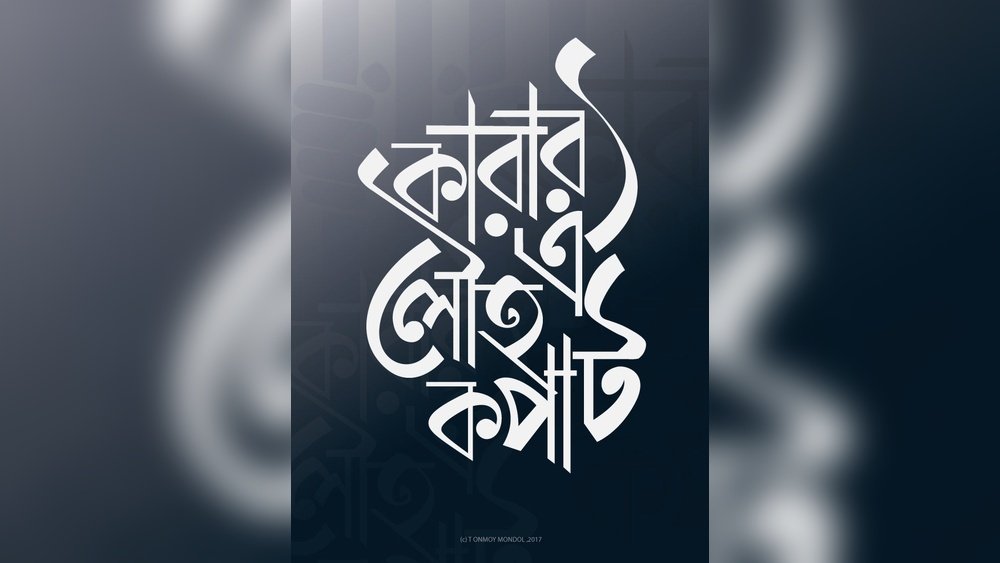
বাংলা ক্যালিগ্রাফি ফন্ট: নান্দনিকতার নতুন অধ্যায়
বাংলা ক্যালিগ্রাফি ফন্ট আমাদের জীবনের নানা ক্ষেত্রে নতুন মাত্রা যোগ করেছে। ডিজিটাল দুনিয়ায় বাংলা লেখা এখন আর শুধু টাইপোগ্রাফি বা সাধারণ টাইপফেসে সীমাবদ্ধ নয়। ক্যালিগ্রাফি ফন্টের মাধ্যমে আমরা এখন বাংলা ভাষার আবেগ, নান্দনিকতা ও শৈল্পিক প্রকাশ সহজেই ফুটিয়ে তুলতে পারি। ক্যালিগ্রাফি মানে শুধু সুন্দর হাতের লেখা নয়—এটি একটি শিল্প। বর্তমান সময়ে ডিজিটাল ডিজাইন, গ্রাফিক্স, সোশ্যাল মিডিয়া পোস্ট, ব্র্যান্ড লোগো, আমন্ত্রণপত্র, বইয়ের প্রচ্ছদ, এমনকি ভিডিও শিরোনামেও বাংলা ক্যালিগ্রাফি ফন্টের জনপ্রিয়তা বাড়ছে।
কিন্তু ক্যালিগ্রাফি ফন্ট বাছাই, ব্যবহার ও এর যথাযথ প্রয়োগ সম্পর্কে সঠিক ধারণা না থাকলে অনেকেই চমৎকার ডিজাইনের সুযোগ হারান। আজকের এই নিবন্ধে বাংলা ক্যালিগ্রাফি ফন্টের ধরন, জনপ্রিয় ফন্ট, ব্যবহার পদ্ধতি, ডিজাইন টিপস, এবং আরও অনেক গুরুত্বপূর্ণ বিষয় নিয়ে বিস্তারিত আলোচনা করা হবে।
বাংলা ক্যালিগ্রাফি ফন্ট কী ও কেন জনপ্রিয়
বাংলা ক্যালিগ্রাফি ফন্ট মানে এমন টাইপফেস, যা হাতে লেখা সুন্দর অক্ষরের আদলে ডিজাইন করা। ক্যালিগ্রাফি ফন্টের মূল বৈশিষ্ট্য হলো এতে হাতে লেখা লেখার প্রাণবন্ততা, আবেগ এবং শৈল্পিকতা দেখা যায়। বাংলার হাজার বছরের সংস্কৃতি, শিল্প ও লোকজ ধারার ছোঁয়া এতে স্পষ্ট। ডিজিটাল যুগে বাংলা লেখার জন্য অনেক স্টাইলের ফন্ট থাকলেও ক্যালিগ্রাফি ফন্ট আলাদা করে চেনা যায় তাদের কারুকার্য ও নান্দনিকতায়।
ক্যালিগ্রাফি ফন্টের জনপ্রিয়তা দ্রুত বাড়ছে, কারণ এর মাধ্যমে বাংলার আবেগ ও সংস্কৃতি আরও সুন্দরভাবে ফুটে ওঠে। ডিজাইন বা বিজ্ঞাপনের ক্ষেত্রে আপনি যখন সাধারণ টাইপফেস ব্যবহার করেন, তখন লেখাটির ভাষা প্রকাশ পেলেও, ক্যালিগ্রাফি ফন্ট ব্যবহারে লেখার ভেতরে বিশেষ ধরনের অনুভূতি, গল্প বা এক্সপ্রেশন চলে আসে। বাংলার উৎসব, সাহিত্য, কিংবা সামাজিক যোগাযোগ মাধ্যম—প্রত্যেক ক্ষেত্রে এই ফন্টের ব্যবহার দিন দিন বাড়ছে।
আরও একটি গুরুত্বপূর্ণ কারণ, ক্যালিগ্রাফি ফন্ট সহজেই চোখে পড়ে এবং মনোযোগ ধরে রাখে। সোশ্যাল মিডিয়ার ভিড়ে আপনার পোস্ট বা ডিজাইন আলাদা হতে চাইলে ক্যালিগ্রাফিক ফন্ট দারুণ কার্যকর। এই ফন্টে বাংলা শব্দগুলো আরও জীবন্ত ও শিল্পগুণে ভরা মনে হয়। অনেকেই কেবল শখের বশে নিজের নাম ক্যালিগ্রাফি ফন্টে লিখে ফেসবুকে বা ইনস্টাগ্রামে শেয়ার করেন। এই চর্চা দিন দিন জনপ্রিয় হচ্ছে।
অনেকে মনে করেন, বাংলা ক্যালিগ্রাফি ফন্ট মানেই শুধু হাতে লেখা স্টাইল। কিন্তু এর চেয়ে বড় ব্যাপার হলো—এতে বাংলার ঐতিহ্য, সংস্কৃতি, লোকজ ছন্দ, আধুনিকতা ও বৈচিত্র্য সব কিছুই একসাথে মিশে যায়। ডিজিটাল মার্কেটিং, ব্র্যান্ডিং, গ্রাফিক ডিজাইন, ভিডিও এডিটিং—সবক্ষেত্রেই এর উপস্থিতি বাড়ছে। শুধু সৌন্দর্যের জন্য নয়, বাংলা ভাষার নিজস্ব আবেগ ও পরিচিতি প্রকাশ করতেও ক্যালিগ্রাফি ফন্ট অপরিহার্য হয়ে উঠেছে।
বাংলা ক্যালিগ্রাফি ফন্টের মূল বৈশিষ্ট্য
ক্যালিগ্রাফি ফন্টের কিছু মৌলিক বৈশিষ্ট্য আছে, যেগুলো সাধারণ টাইপফেস থেকে একে আলাদা করে। এই বৈশিষ্ট্যগুলো জানলে ফন্ট বাছাইয়ে সুবিধা হবে এবং ডিজাইনেও নতুনত্ব আসবে।
- হাতে লেখা স্টাইল: ক্যালিগ্রাফি ফন্টের অক্ষর দেখতে মনে হয়, যেন কারও হাতে লেখা। এতে লেখার ভেতরে প্রাণ ও নান্দনিকতা চলে আসে। এই হাতে লেখা স্টাইল কখনও সোজা, কখনও বাঁকা, কখনও আবার একটু এলোমেলোও হতে পারে।
- স্ট্রোকের ভিন্নতা: বাংলা ক্যালিগ্রাফি ফন্টে মোটা ও পাতলা স্ট্রোকের মিশ্রণ থাকে। কিছু অক্ষরের শুরুতে বা শেষে স্ট্রোক মোটা, কিছু অক্ষরের মাঝে পাতলা রেখা দেখা যায়। এই বৈচিত্র্য পুরো লেখাকে আরও আকর্ষণীয় করে তোলে।
- লতাপাতা বা অলঙ্করণ: অনেক ক্যালিগ্রাফি ফন্টে অক্ষরের সাথে লতাপাতা, ফ্লাওয়ার, বা বিভিন্ন অলঙ্কার যোগ করা হয়। এগুলো কখনও অক্ষরের নিচে, কখনও পাশে, কখনও পুরো লেখার চারপাশে থাকে। এই অলঙ্করণ বাংলা ক্যালিগ্রাফি ফন্টের এক বিশেষ বৈশিষ্ট্য।
- কিছুটা অসমতা: সাধারণ টাইপফেসে সব অক্ষর একরকম, কিন্তু ক্যালিগ্রাফি ফন্টে কখনও কখনও এক অক্ষরের রূপ আরেক অক্ষরের থেকে একটু আলাদা হয়। এই অসমতা লেখাকে আরও স্বতঃস্ফূর্ত ও শিল্পময় করে তোলে। এতে হাতে লেখা ‘ইম্পারফেকশন’-এর সৌন্দর্য ফুটে ওঠে।
- নান্দনিক স্পেসিং: অক্ষরের মাঝে ও লাইনের মাঝে ফাঁকা জায়গা যত্ন নিয়ে ঠিক করা হয়। এতে পুরো লেখার ভারসাম্য (balance) বজায় থাকে। স্পেসিং ঠিক না হলে ফন্ট দেখতে অগোছালো লাগতে পারে।
- বৈচিত্র্যপূর্ণ যুক্তাক্ষর: অনেক ক্যালিগ্রাফি ফন্টে বিশেষভাবে ডিজাইন করা যুক্তাক্ষর থাকে। এতে ফন্টের ইউনিকনেস বাড়ে, এবং বাংলা লেখার জটিলতা আরও সহজভাবে প্রকাশ করা যায়।
- মানানসই মাত্রা ও কার: বাংলা ভাষায় ‘মাত্রা’ ও ‘কার’ খুব গুরুত্বপূর্ণ। ক্যালিগ্রাফি ফন্টে এগুলোকে আরও সুন্দর ও নান্দনিকভাবে উপস্থাপন করা হয়। কখনও মাত্রা একটু বাঁকা বা ফুলের মতো আকৃতিতে থাকে।
এছাড়া, ক্যালিগ্রাফি ফন্টে কখনও কখনও অক্ষরের শুরুর দিকে বা শেষে বিশেষ ধরনের টেইল, সুইশ, বা কার্ভ যোগ করা হয়, যা লেখাকে আরও স্টাইলিশ করে তোলে।
জনপ্রিয় বাংলা ক্যালিগ্রাফি ফন্টসমূহ
বাংলা ক্যালিগ্রাফি ফন্টের সংখ্যা দিন দিন বাড়ছে এবং এর বৈচিত্র্যও ক্রমশ বৃদ্ধি পাচ্ছে। বর্তমানে কিছু ফন্ট ডিজাইনার ও ডিজাইন প্ল্যাটফর্ম দারুণ সুন্দর ও ইউনিক ক্যালিগ্রাফি ফন্ট তৈরি করছেন। এখানে সবচেয়ে জনপ্রিয় ও বহুল ব্যবহৃত কিছু ফন্ট নিয়ে বিস্তারিত আলোচনা করা হলো, যাতে আপনি আপনার ডিজাইনের জন্য সঠিক ফন্ট বাছাই করতে পারেন।
১. ক্যালিগ্রাফি বাংলা
‘ক্যালিগ্রাফি বাংলা’ ফন্টটি ডিজাইন জগতে একটি সুপরিচিত নাম। এই ফন্টে আপনি পেয়ে যাবেন হাতে লেখা স্টাইলের নিখুঁত প্রতিচ্ছবি। অক্ষরের মধ্যে মোটা-পাতলা স্ট্রোকের অসাধারণ কম্বিনেশন, কিছু অক্ষরে হালকা অলঙ্করণ, এবং বর্ণের মাঝে ভারসাম্যপূর্ণ স্পেসিং—সব মিলিয়ে এটি খুবই পেশাদার মানের ফন্ট। সোশ্যাল মিডিয়া পোস্ট, ডিজিটাল ব্যানার, বা ব্র্যান্ড লোগো ডিজাইনে এই ফন্টটি ব্যাপকভাবে ব্যবহৃত হয়।
অনেক ডিজাইনার এই ফন্ট পছন্দ করেন কারণ, এটি খুব সহজেই চোখে পড়ে এবং বাংলা ভাষার আবেগ প্রকাশে কার্যকর। বিশেষ করে, লেখার শুরু ও শেষের স্ট্রোকগুলোতে হাতে লেখা ফ্লো স্পষ্টভাবে দেখা যায়। আপনি চাইলে এই ফন্ট বিভিন্ন কালারে ব্যবহার করতে পারেন এবং একই ডিজাইনকেও ভিন্নভাবে উপস্থাপন করতে পারবেন।
২. জ্যোতি ক্যালিগ্রাফি
‘জ্যোতি ক্যালিগ্রাফি’ ফন্টের অক্ষরগুলো দেখতে অনেকটা ব্রাশ দিয়ে আঁকা মনে হয়। এতে রয়েছে মুক্তভাবে আঁকা স্টাইল, যেখানে কিছু অক্ষর একটু বাঁকা, কিছুটা ঢেউ খেলানো। এই ফন্ট বিশেষভাবে সাহিত্য ম্যাগাজিন, পত্রিকা কিংবা আমন্ত্রণপত্রে ব্যবহার হয়। ব্রাশ স্ট্রোকের নান্দনিক বৈচিত্র্য, সাথে অক্ষরের মাঝে নরম স্পেসিং—সব মিলিয়ে এটি অনেকের পছন্দের তালিকায়।
জ্যোতি ক্যালিগ্রাফি ফন্টের আরেকটি বিশেষ দিক হলো—এতে যুক্তাক্ষর ও মাত্রা খুব সুন্দরভাবে ফুটে ওঠে। ফলে, আপনি যদি বড় আকারের শিরোনাম বা কবিতার জন্য ফন্ট খুঁজছেন, এটি হতে পারে আদর্শ পছন্দ।
৩. বাংলা ক্যালিগ্রাফি স্টাইল
এটি একটি ফ্রি ফন্ট, যা আপনি Fontlipi থেকে সহজেই ডাউনলোড করতে পারেন। এই ফন্টে আধুনিক ডিজাইনের ছোঁয়া থাকলেও, ক্লাসিক ক্যালিগ্রাফির সৌন্দর্য বজায় আছে। অক্ষরগুলো সাধারণত একটু লম্বা, এবং স্ট্রোকের মধ্যে হালকা কার্ভ বা বাঁক দেখা যায়। ডিজিটাল আর্ট, পোস্টার ডিজাইন, বা সোশ্যাল মিডিয়া থাম্বনেইলে এটি দারুণ মানানসই।
ফন্টটির ফ্রি ভার্সন থাকায়, নতুন ডিজাইনার বা শিক্ষার্থীরাও সহজে এটি ব্যবহার করতে পারেন। এছাড়া, ফন্টের ফাইল ছোট এবং ইনস্টল করা সহজ।
Read Also: মাহফুজ লিপি বাংলা প্রিমিয়াম ফন্ট: স্টাইলিশ এবং প্রফেশনাল ডিজাইন
৪. রঙিন ক্যালিগ্রাফি
‘রঙিন ক্যালিগ্রাফি’ ফন্টে অক্ষরগুলো স্পষ্ট ও বড়, বিশেষ করে শিরোনাম বা হেডিং ডিজাইনের জন্য তৈরি। এই ফন্টের বিশেষত্ব হলো—কিছু অক্ষরের নিচে বা পাশে আলংকারিক ডিজাইন (যেমন লতাপাতা, ফুল) দেয়া থাকে, যা সাধারণ ফন্ট থেকে একে আলাদা করে। পোস্টার, ব্যানার, ম্যাগাজিনের হেডিং কিংবা ইউটিউব ভিডিওর নাম লেখার জন্য এটি বেশ উপযোগী।
এটি ব্যবহার করলে আপনার ডিজাইন অনেক বেশি আকর্ষণীয় হবে, তবে বডি টেক্সটে ব্যবহার করলে পড়তে একটু কষ্ট হতে পারে।
৫. আর্টিস্টিক বাংলা
এই ফন্টটি হাতে লেখা অনুভূতি দেয় এবং ব্রাশ স্ট্রোকের মতো মোটা-পাতলা লাইনের মিশ্রণ রয়েছে। অক্ষরগুলো দেখতে একটু এলোমেলো, কিন্তু তাতেই রয়েছে শিল্প-সৌন্দর্য। পোস্টার, ব্যানার, আর্ট ওয়ার্ক—এই সব ডিজাইনেই এটি আদর্শ। বিশেষ করে, যারা হাতে লেখা চিঠি বা কবিতার অনুভূতি ডিজাইনে আনতে চান, তাদের জন্য এই ফন্ট অসাধারণ।
এছাড়া, এই ফন্টটি ছোট বা বড়—যেকোনো সাইজে ব্যবহার করা যায় এবং অক্ষরের স্পেসিংও খুব সুন্দরভাবে ডিজাইন করা।
৬. স্টাইলিশ ক্যালিগ্রাফি
‘স্টাইলিশ ক্যালিগ্রাফি’ ফন্ট আধুনিক ও ট্র্যাডিশনাল ক্যালিগ্রাফি ঢঙের মিশ্রণ। ডিজিটাল বিজ্ঞাপন, সোশ্যাল মিডিয়া পোস্ট, ইউটিউব থাম্বনেইল, কিংবা ব্র্যান্ড লোগো—সবক্ষেত্রেই এটি কার্যকর। এই ফন্টের অক্ষরগুলো একটু টুইস্টেড, কিছু অক্ষরে স্টাইলিশ কার্ভ বা সুইশ আছে। ফলে, আপনি চাইলে একই ফন্ট দিয়ে একাধিক ডিজাইন স্টাইল তৈরি করতে পারবেন।
৭. হস্তলিপি ক্যালিগ্রাফি
এটি মূলত হাতে লেখা স্টাইলের ওপর ভিত্তি করে তৈরি। অক্ষরগুলো দেখতে মনে হবে, যেন কেউ দ্রুত অথচ সুন্দরভাবে লিখেছে। ব্যক্তিগত আমন্ত্রণপত্র, কবিতা, চিঠির ডিজাইন কিংবা সোশ্যাল মিডিয়া কোটেশন—সবক্ষেত্রেই এই ফন্ট মানানসই। এই ফন্ট ব্যবহার করলে ডিজাইনে ব্যক্তিগত স্পর্শ (personal touch) আসে।
৮. ডিজাইন বাংলা ক্যালিগ্রাফি
এখানে ক্লাসিক ও মডার্ন স্টাইলের মিশ্রণ রয়েছে। অক্ষরগুলোতে মাঝে মাঝে অতিরিক্ত অলঙ্করণ থাকলেও পড়তে সহজ। তাই সোশ্যাল মিডিয়া গ্রাফিক্স, ওয়েবসাইট হেডার, বিজ্ঞাপন ডিজাইন—সবখানেই এটি ব্যবহৃত হয়। ফন্টের ভারসাম্যপূর্ণ স্পেসিং এবং ইউনিক স্টাইলের কার্ভ ডিজাইনকে আরও আকর্ষণীয় করে তোলে।
৯. ব্রাশ ক্যালিগ্রাফি বাংলা
ব্রাশ দিয়ে আঁকা অক্ষরের মতো এই ফন্টের ডিজাইন। মোটা ও পাতলা স্ট্রোকের অসাধারণ কম্বিনেশন, এবং অক্ষরের মাঝে নান্দনিক স্পেসিং, ফলে ডিজিটাল আর্ট, ফটো এডিটিং, বা ভিডিও শিরোনামে এটি জনপ্রিয়। বিশেষ করে, যারা হাতে লেখা ব্রাশ-স্টাইল ফন্ট পছন্দ করেন, তাদের জন্য এটি আদর্শ।
১০. ইউনিক বাংলা ক্যালিগ্রাফি
প্রতিটি অক্ষরে ইউনিকনেস আছে। সাধারণত ব্র্যান্ড লোগো, টাইটেল ডিজাইন, বইয়ের প্রচ্ছদ, বা বিশেষ দিবসের পোস্টে ব্যবহৃত হয়। এই ফন্টের বিশেষত্ব হলো—একই অক্ষর বারবার হলেও, প্রতিবার নতুনভাবে ডিজাইন করা। ফলে, পুরো লেখাটা দেখতে আরও শিল্পময় লাগে।
বাংলা ক্যালিগ্রাফি ফন্ট নির্বাচন করার নিয়ম
সঠিক ফন্ট নির্বাচন ডিজাইনের জন্য খুব গুরুত্বপূর্ণ। অনেক সময় দেখা যায়, সুন্দর লেখার চেয়ে উপযোগী ফন্ট বেছে নেওয়াই আসল চ্যালেঞ্জ। ফন্টের সৌন্দর্য যেমন গুরুত্বপূর্ণ, তেমনি তার ব্যবহারিক দিকও বুঝে নিতে হয়। নিচে কিছু গুরুত্বপূর্ণ বিষয় তুলে ধরা হলো—
| বিষয় | কেন গুরুত্বপূর্ণ | পরামর্শ |
|---|---|---|
| ফন্টের পাঠযোগ্যতা | অত্যন্ত অলঙ্কারিক ফন্ট পড়তে সমস্যা হতে পারে | শিরোনাম ও ছোট লেখার জন্য ভিন্ন ফন্ট ব্যবহার করুন |
| উপযুক্ততা | সব ফন্ট সব ডিজাইনে মানায় না | কাজের ধরন অনুযায়ী ফন্ট বাছাই করুন |
| ফাইল ফরম্যাট | কিছু সফটওয়্যারে নির্দিষ্ট ফরম্যাটই সাপোর্ট করে | OTF/TTF ফরম্যাট সাধারণত বেশি ব্যবহারযোগ্য |
| লাইসেন্স | সব ফন্ট ফ্রি নয় | ব্যবহারের আগে লাইসেন্স চেক করুন |
নতুনদের জন্য দুইটি মূল্যবান টিপস
- অনেকেই শুধু সুন্দর দেখলেই ফন্ট বাছাই করেন। কিন্তু আসল কাজের জন্য ফন্টটি উপযোগী কিনা, সেই দিকটি খেয়াল করতে ভুলে যান। যেমন, বড় টেক্সটে অতিরিক্ত অলঙ্কার থাকলে পড়তে কষ্ট হয়।
- ফন্টের ভার্সন বা ফরম্যাট না মিললে অনেক সফটওয়্যারে ফন্ট সাপোর্ট নাও করতে পারে। তাই ডাউনলোড করার সময় আপনার সফটওয়্যারের উপযোগী ফরম্যাটটি বাছাই করুন।
আরেকটি গুরুত্বপূর্ণ বিষয়, ফন্ট নির্বাচনের সময় তার ফ্যামিলি, ওজন (weight), এবং ভার্সন দেখুন। অনেক সময় এক ফন্টের একাধিক ভার্সন থাকে—সেগুলো পরীক্ষা করে সেরা ভার্সনটি বাছাই করুন।
Credit: www.freepik.com
বাংলা ক্যালিগ্রাফি ফন্ট কোথায় পাবেন?
বর্তমানে অসংখ্য ওয়েবসাইটে ফ্রি ও প্রিমিয়াম বাংলা ক্যালিগ্রাফি ফন্ট পাওয়া যায়। ডিজাইন জগতে এই ওয়েবসাইটগুলো অনেক জনপ্রিয় কারণ, এখানে ফন্টের বৈচিত্র্য, মান, ও আপডেট সবই ভালো থাকে। কিছু সেরা সোর্স—
- Fontlipi (বেশিরভাগ ফ্রি ও মানসম্পন্ন ফন্ট)
- Google Fonts (বাংলা ফন্টের সংখ্যা কম, তবে কিছু ক্যালিগ্রাফি ফন্ট আছে)
- Behance (কিছু ফ্রি, কিছু পেইড ফন্ট)
- Creative Market (প্রিমিয়াম ফন্ট)
এছাড়াও, বিভিন্ন ফেসবুক গ্রুপ, ডিজাইন ফোরাম এবং টেলিগ্রাম চ্যানেলেও অনেক নতুন ফন্ট শেয়ার হয়। তবে, সব সময় অফিসিয়াল ওয়েবসাইট থেকে ডাউনলোড করা নিরাপদ।
Related: Bijoy Bangla Font Free Download: দ্রুত ও সহজ ফন্ট সংগ্রহ করুন!
ডাউনলোড করার সময় দেখুন, ফন্টটি ফ্রি, ফ্রি ফর কমার্শিয়াল ইউজ, না কি শুধু ব্যক্তিগত ব্যবহারের জন্য। লাইসেন্সের শর্ত জেনে নিন, কারণ অনেক সময় বাণিজ্যিক কাজে ব্যবহারে ক্রেডিট বা অনুমতি লাগতে পারে।
কিভাবে বাংলা ক্যালিগ্রাফি ফন্ট ব্যবহার করবেন
ডিজাইন সফটওয়্যারে বাংলা ক্যালিগ্রাফি ফন্ট ব্যবহার করা খুব সহজ। এখানে ধাপে ধাপে বর্ণনা করা হলো—
- প্রথমে পছন্দের ফন্টটি ডাউনলোড করুন (সাধারণত .zip ফাইল, ভিতরে .ttf বা .otf ফরম্যাটে)।
- ফন্ট ফাইলটি ওপেন করে ‘ইনস্টল’ বোতামে ক্লিক করুন।
- ইনস্টল হলে ফন্টটি স্বয়ংক্রিয়ভাবে আপনার কম্পিউটারের ফন্ট লিস্টে যুক্ত হবে।
- আপনার পছন্দের ডিজাইন সফটওয়্যার (যেমন: Photoshop, Illustrator, MS Word, Canva) ওপেন করুন।
- ফন্ট লিস্ট থেকে নতুন ক্যালিগ্রাফি ফন্টটি খুঁজে নিন এবং প্রয়োজনে সেট করুন।
- বাংলা কীবোর্ড ব্যবহার করে সহজেই লিখতে পারবেন।
উদাহরণ:
আপনি যদি Photoshop-এ নতুন ফন্ট ব্যবহার করতে চান, তাহলে প্রথমে ফন্ট ইন্সটল করে নিন। তারপর Photoshop ওপেন করলে ফন্ট লিস্টে নতুন ক্যালিগ্রাফি ফন্ট দেখা যাবে। বাংলা ভাষায় টাইপ করতে চাইলে বিজয়, অভ্র বা ইউনিজয় কীবোর্ড ব্যবহার করুন।
মোবাইলে ক্যালিগ্রাফি ফন্ট ব্যবহার
এন্ড্রয়েড বা আইফোনে কাস্টম ফন্ট ব্যবহারের জন্য কিছু অ্যাপ যেমন Phonto, Pixellab, Canva ইত্যাদি ব্যবহার করা যায়। অ্যাপে ফন্ট ইমপোর্ট অপশন থাকে। আপনি ফন্ট ফাইল ডাউনলোড করে অ্যাপে ইমপোর্ট করুন। এরপর ছবিতে বা ডিজাইনে সহজেই বাংলা ক্যালিগ্রাফি ফন্টে লিখতে পারবেন।
তবে, মোবাইলের সিস্টেম লেভেলে (অর্থাৎ পুরো ডিভাইসে) সাধারণত ফন্ট পরিবর্তন করা যায় না। কিছু কাস্টম লঞ্চার বা থিম ইঞ্জিনে ফন্ট চেঞ্জ করার অপশন থাকলেও, তা সব ফোনে কাজ নাও করতে পারে।
ফন্ট ইনস্টল করতে সমস্যা হলে কী করবেন?
- ফন্ট ফাইলটি ঠিকমতো ডাউনলোড হয়েছে কি না চেক করুন।
- ফাইলটি .ttf বা .otf ফরম্যাটে আছে কি না দেখুন।
- সফটওয়্যার বা অপারেটিং সিস্টেম আপডেট থাকলে ফন্ট ইন্সটল সহজ হয়।
- প্রয়োজনে ফন্টটি আবার ডাউনলোড করে ইনস্টল করুন।
বাংলা ক্যালিগ্রাফি ফন্টের ডিজাইন টিপস
ডিজাইনে ক্যালিগ্রাফি ফন্টের ব্যবহার মানেই নান্দনিকতা, তবে কিছু ভুল করলে পুরো ডিজাইন নষ্ট হতে পারে। আপনার ডিজাইন পেশাদার ও আকর্ষণীয় করতে চাইলে নিচের টিপসগুলো মানুন—
- মাত্রা ও স্পেসিং ঠিক রাখুন: ক্যালিগ্রাফি ফন্টে অনেক সময় অক্ষরের মাঝে বেশি বা কম স্পেস থেকে যায়। লিখার আগে ও পরে সব অক্ষর একবার দেখে নিন। বিশেষ করে, যুক্তাক্ষর ও মাত্রা ঠিকমতো দেখা যাচ্ছে কি না নিশ্চিত করুন।
- একাধিক ক্যালিগ্রাফি ফন্ট একসাথে ব্যবহার করবেন না: অনেকেই মনে করেন, একাধিক ক্যালিগ্রাফি ফন্ট এক ডিজাইনে দিলে আরও সুন্দর লাগবে। আসলে এতে ডিজাইন এলোমেলো হয়ে যায় এবং পাঠযোগ্যতা কমে যায়।
- কালার কনট্রাস্ট: ব্যাকগ্রাউন্ড ও ফন্টের রঙে যথেষ্ট কনট্রাস্ট রাখুন। ক্যালিগ্রাফি ফন্ট সাধারণত মোটা-পাতলা স্ট্রোকে হয়, ফলে হালকা রঙের ব্যাকগ্রাউন্ডে গাঢ় রঙের ফন্ট বা উল্টোটা ব্যবহার করুন।
- শিরোনাম ও বডি টেক্সটে ভিন্ন ফন্ট: ক্যালিগ্রাফি ফন্ট সাধারণত শিরোনামের জন্য ভালো; বডি টেক্সটে সাধারণ ফন্ট ব্যবহার করুন। এতে পাঠযোগ্যতা বাড়ে এবং ডিজাইন আরও ভারসাম্যপূর্ণ হয়।
- অলঙ্করণ বা লতাপাতা ব্যবহার: ফন্টে যদি অতিরিক্ত অলঙ্করণ থাকে, তবে ডিজাইনে কম ব্যবহার করুন। বেশি অলঙ্করণ হলে ফন্ট পড়তে কষ্ট হয় এবং ডিজাইন অগোছালো দেখায়।
- ড্রপ শ্যাডো বা গ্লো এফেক্ট যুক্ত করুন: ক্যালিগ্রাফি ফন্টের সৌন্দর্য বাড়াতে হালকা ড্রপ শ্যাডো, গ্লো বা আউটলাইন এফেক্ট দিতে পারেন। তবে খুব বেশি দিলে লেখা পড়তে কষ্ট হবে।
- ফন্ট সাইজ ঠিক রাখুন: শিরোনামে বড় ফন্ট ব্যবহার করুন, কিন্তু বেশি বড় করলে স্ট্রোক ব্লার হতে পারে। বডি টেক্সটে ছোট ফন্ট ব্যবহার করবেন না।
- স্পেশাল ক্যারেক্টার ও সিম্বল ব্যবহার: ক্যালিগ্রাফি ফন্টে অনেক সময় স্পেশাল ক্যারেক্টার (যেমন: ফুল, তারা, ইমোজি) আলাদাভাবে যুক্ত থাকে। প্রয়োজনে সেগুলোও ব্যবহার করতে পারেন।
সাধারণ ভুল-ত্রুটি থেকে কীভাবে এড়াবেন?
- লিখার আগে সব অক্ষর টাইপ করে দেখে নিন।
- অলঙ্করণ বেশি থাকলে ফন্ট এড়িয়ে চলুন।
- পুরো ডিজাইন শেষে একবার পড়ে দেখুন—সবকিছু ঠিক আছে কি না।
বাংলা ক্যালিগ্রাফি ফন্টের ব্যবহার ক্ষেত্র
বাংলা ক্যালিগ্রাফি ফন্ট এখন শুধু গ্রাফিক ডিজাইনের গণ্ডিতে সীমাবদ্ধ নেই। নানান ক্ষেত্রে এ ফন্টের ব্যবহার দ্রুত বাড়ছে। কিছু প্রধান ক্ষেত্র—
- বিজ্ঞাপন ও ডিজিটাল ব্যানার: বিজ্ঞাপনের মূল লক্ষ্যই হলো মানুষের দৃষ্টি আকর্ষণ করা। ক্যালিগ্রাফি ফন্টে হেডিং, ট্যাগলাইন, বা অফার লিখলে তা সহজেই চোখে পড়ে। বিশেষ করে ই-কমার্স ব্যানার, ডিসকাউন্ট ক্যাম্পেইন, বা নতুন পণ্যের বিজ্ঞাপনে ক্যালিগ্রাফি ফন্ট জনপ্রিয়।
- সোশ্যাল মিডিয়া পোস্ট: ফেসবুক, ইনস্টাগ্রাম, ইউটিউব থাম্বনেইল, কিংবা স্টোরি ডিজাইনে বাংলা ক্যালিগ্রাফি ফন্ট ব্যাপকভাবে ব্যবহৃত হচ্ছে। এতে পোস্টে ইউনিকনেস আসে এবং ফলোয়ারেরা সহজেই আকৃষ্ট হন।
- বইয়ের প্রচ্ছদ ও ম্যাগাজিন: বইয়ের নাম, লেখকের নাম, বা ম্যাগাজিনের বিশেষ শিরোনাম ক্যালিগ্রাফি ফন্টে লিখলে প্রচ্ছদ আরও আকর্ষণীয় হয়। বিশেষ করে কবিতা বা সাহিত্যের বইয়ে হাতে লেখা ক্যালিগ্রাফি ফন্টের চাহিদা বেশি।
- বিবাহের কার্ড, আমন্ত্রণপত্র: পারিবারিক বা সামাজিক অনুষ্ঠানের কার্ডে হাতে লেখা ক্যালিগ্রাফি ফন্ট ব্যবহার করলে কার্ডটি আরও পার্সোনাল ও সৌন্দর্যপূর্ণ হয়। জন্মদিন, বিবাহ, পূজা, ঈদের কার্ড—সবক্ষেত্রেই এই ফন্ট জনপ্রিয়।
- লোগো ও ব্র্যান্ডিং: ব্যবসার লোগো বা পণ্যের নাম ক্যালিগ্রাফি ফন্টে লিখলে তা সহজেই মানুষের মনে গেঁথে যায়। অনেক ফ্যাশন হাউজ, রেস্টুরেন্ট, বা লাইফস্টাইল ব্র্যান্ড বাংলা ক্যালিগ্রাফি ফন্ট ব্যবহার করছে।
- ভিজুয়াল আর্ট ও কন্টেন্ট ক্রিয়েশন: ডিজিটাল আর্ট, পোস্টার, ভিডিও শিরোনাম, মিউজিক ভিডিও—সব ক্ষেত্রেই ক্যালিগ্রাফি ফন্ট ব্যবহৃত হচ্ছে। এতে কনটেন্টের মান ও আকর্ষণ দুই-ই বাড়ে।
বিশেষ উদাহরণ
- হুমায়ূন আহমেদের বইয়ের প্রচ্ছদে ক্যালিগ্রাফি ফন্টের আধিপত্য স্পষ্ট।
- ফ্যাশন হাউজ ‘নক্ষত্র’, রেস্টুরেন্ট ‘কৃষ্ণচূড়া’ ইত্যাদির লোগোতে ক্যালিগ্রাফি ফন্ট ব্যবহৃত হয়েছে।
- ঈদ, পূজা, কিংবা বিশেষ দিবসে সোশ্যাল মিডিয়ায় শুভেচ্ছা পোস্টে ক্যালিগ্রাফি ফন্ট খুব জনপ্রিয়।
Credit: bits.poetry.blog
বাংলা ক্যালিগ্রাফি ফন্টের সীমাবদ্ধতা ও চ্যালেঞ্জ
ক্যালিগ্রাফি ফন্ট ব্যবহারে কিছু সীমাবদ্ধতা ও চ্যালেঞ্জ রয়েছে। এগুলো জানলে ডিজাইন করতে সুবিধা হবে এবং ভুল কম হবে।
- সব অক্ষরের সঠিক রেন্ডারিং হয় না: অনেক ক্যালিগ্রাফি ফন্টে যুক্তাক্ষর, কার, মাত্রা ঠিকমতো দেখা যায় না। ফলে লেখার মাঝে অক্ষর কাটা বা অদ্ভুত দেখাতে পারে।
- ডিভাইস বা সফটওয়্যার সাপোর্টের সীমাবদ্ধতা: কিছু পুরনো সফটওয়্যারে ক্যালিগ্রাফি ফন্ট কাজ করে না বা সঠিকভাবে শো করে না। বিশেষ করে, এডিটিং সফটওয়্যারের আপডেট ভার্সন না হলে অনেক ফিচার কাজ নাও করতে পারে।
- ফন্ট সাইজ বড় করলে কোয়ালিটি কমে যেতে পারে: সব ক্যালিগ্রাফি ফন্ট ভেক্টর ভিত্তিক নয়। ফলে, বড় সাইজে ব্যবহার করলে ফন্ট ব্লার বা পিক্সেলেটেড হতে পারে।
- কিছু ফন্টে লাইসেন্স ঝামেলা: অনেক ফন্ট ফ্রি মনে হলেও, বাণিজ্যিক কাজে ব্যবহারে আলাদা অনুমতি বা ক্রেডিট দিতে হয়। লাইসেন্স না দেখলে আইনি ঝামেলায় পড়ার আশঙ্কা থাকে।
- আলাদা ওজন (weight) ও স্টাইলের অভাব: অনেক ক্যালিগ্রাফি ফন্টে শুধু একটি স্টাইল থাকে—বোল্ড, লাইট, ইটালিক ভার্সন থাকে না। এতে ডিজাইন ফ্লেক্সিবিলিটি কমে যায়।
সমাধান কী?
- ফন্ট বাছাইয়ের সময় অক্ষরের নমুনা ও যুক্তাক্ষর চেক করুন।
- OTF বা TTF ফরম্যাটের ফন্ট বাছাই করুন, কারণ এগুলো বেশি সফটওয়্যার সাপোর্ট করে।
- ফ্রি ও ওপেন সোর্স ফন্ট ব্যবহার করুন যাতে লাইসেন্স ঝামেলা না হয়।
- ডিজাইনের জন্য সর্বদা আপডেটেড সফটওয়্যার ব্যবহার করুন।
- ফন্টের ডেভেলপার বা ডিজাইনারের সাথে যোগাযোগ করে বাণিজ্যিক ব্যবহারের অনুমতি নিন।
বাংলা ক্যালিগ্রাফি ফন্টের ভবিষ্যৎ
ডিজিটাল বাংলাদেশে ক্যালিগ্রাফি ফন্টের চাহিদা দ্রুত বাড়ছে। ডিজিটাল মার্কেটিং, ই-কমার্স, সোশ্যাল মিডিয়া, অনলাইন ব্র্যান্ডিং—সবখানেই বাংলা ক্যালিগ্রাফি ফন্ট ব্যবহারের সুযোগ বাড়ছে। এখন অনেক তরুণ ডিজাইনার নতুন নতুন ক্যালিগ্রাফি ফন্ট তৈরি করছেন। ফন্ট ডিজাইনের জন্য বিভিন্ন সফটওয়্যার, যেমন Adobe Illustrator, FontForge, Glyphs ইত্যাদি সহজলভ্য হয়েছে।
আর্টিফিশিয়াল ইন্টেলিজেন্স ও অটোমেটেড ডিজাইন টুলসের কারণে ফন্ট ডিজাইন এখন আরও সহজ হয়েছে। ভবিষ্যতে প্রত্যেকেই নিজের হাতে লেখা বা নিজস্ব স্টাইলের ক্যালিগ্রাফি ফন্ট বানাতে পারবেন। বাংলা ভাষার জন্য ইউনিকনেস ও বৈচিত্র্য আরও বাড়বে। এছাড়া, ফন্টে অ্যানিমেশন, থ্রি-ডি, ইন্টারেকটিভ ভার্সন—এসবও জনপ্রিয় হবে।
একটি বিশেষ দিক হলো, অনেক স্কুল, কলেজ, বিশ্ববিদ্যালয় এখন বাংলা ক্যালিগ্রাফি ফন্ট দিয়ে পোস্টার বা ডিজিটাল কনটেন্ট তৈরি করছে। ফলে, শিক্ষার্থীরা ছোটবেলা থেকেই বাংলা ভাষার নান্দনিকতা ও ক্যালিগ্রাফি শেখার সুযোগ পাচ্ছে।
বাংলা ক্যালিগ্রাফি ফন্ট: তুলনামূলক বিশ্লেষণ
নিচে কয়েকটি জনপ্রিয় ক্যালিগ্রাফি ফন্টের তুলনামূলক তথ্য দেয়া হলো, যাতে আপনি সহজেই বুঝতে পারেন কোন ফন্ট কোন কাজে উপযোগী—
Check Out: Nikosh Bangla Font Download: দ্রুত ও সহজ ফন্ট সংগ্রহ করুন
| ফন্টের নাম | স্টাইল | ব্যবহার ক্ষেত্র | লাইসেন্স |
|---|---|---|---|
| ক্যালিগ্রাফি বাংলা | ক্লাসিক হ্যান্ডরাইটিং | লোগো, হেডিং, পোস্টার | ফ্রি (ব্যক্তিগত) |
| জ্যোতি ক্যালিগ্রাফি | ব্রাশ স্ট্রোক | বই, আমন্ত্রণপত্র | ফ্রি/পেইড |
| ডিজাইন বাংলা ক্যালিগ্রাফি | মডার্ন-ট্র্যাডিশনাল | ওয়েব, সোশ্যাল মিডিয়া | ফ্রি |
| রঙিন ক্যালিগ্রাফি | অলঙ্করণ যুক্ত | শিরোনাম, আর্ট ওয়ার্ক | ফ্রি |
এই তুলনামূলক বিশ্লেষণ দেখে বুঝতে পারবেন, কোন ফন্ট কোথায় বেশি মানানসই। ডিজাইনের উদ্দেশ্য বুঝে সঠিক ফন্ট বাছাই করুন।
বাংলা ক্যালিগ্রাফি ফন্টের চিত্র উদাহরণ
আপনি চাইলে Fontlipi ক্যালিগ্রাফি ফন্ট গ্যালারিতে প্রবেশ করে বিভিন্ন ফন্টের নমুনা ও ছবি দেখতে পারবেন। ফন্টের উদাহরণ দেখতে চাইলে প্রতিটি ফন্টের পাশে ‘Preview’ বা ‘নমুনা’ বাটন ক্লিক করুন। এতে আপনি সহজেই বুঝতে পারবেন, কোন ফন্টটি আপনার ডিজাইনের জন্য উপযুক্ত।
ডিজাইন করার আগে বিভিন্ন ফন্টের চিত্র নমুনা পরীক্ষা করলে ভুল কম হবে এবং ডিজাইন আরও পেশাদার হবে।
Credit: www.almamunhossen.com
বাংলা ক্যালিগ্রাফি ফন্ট নিয়ে সাধারণ ভুল-ত্রুটি
- অতিরিক্ত অলঙ্করণে আসক্তি: অনেকেই অলঙ্করণ বেশি থাকলেই ফন্টটি বেছে নেন, ফলে পাঠযোগ্যতা কমে যায়।
- বডি টেক্সটে ক্যালিগ্রাফি ফন্ট ব্যবহার: পুরো পোস্ট বা বইয়ে ক্যালিগ্রাফি ফন্ট দিলে পড়তে কষ্ট হয়।
- ফন্ট লাইসেন্স না দেখা: ফ্রি মনে হলেও অনেক ফন্টে বাণিজ্যিক ব্যবহারে অনুমতি প্রয়োজন।
- ফন্ট কম্প্যাটিবিলিটি না দেখা: সফটওয়্যার সাপোর্ট করে কিনা—এটা না দেখে ফন্ট ডাউনলোড করা।
আরও একটি ভুল—ডিজাইন শেষে ফন্ট চেঞ্জ করলে অনেক সময় অক্ষরের ফর্মেটিং নষ্ট হয়ে যায়। তাই, ফাইনাল ডিজাইন করার আগে ফন্ট নিশ্চিত করুন।
বাংলা ক্যালিগ্রাফি ফন্টের নতুনত্ব: নিজের হাতে ফন্ট তৈরি
বর্তমানে অনেক ডিজাইনার নিজের হাতে লেখা স্টাইল থেকে কাস্টম ফন্ট তৈরি করছেন। আপনি চাইলে অনলাইন টুল যেমন Calligraphr ব্যবহার করে নিজের ক্যালিগ্রাফি ফন্ট বানিয়ে নিতে পারেন। প্রথমে কাগজে অক্ষরগুলো লিখে স্ক্যান করুন, এরপর সফটওয়্যারে আপলোড করুন। সফটওয়্যার নিজে থেকেই আপনার হাতে লেখা অক্ষর থেকে ফন্ট বানিয়ে দেবে।
এটি একদিকে আপনার ব্যক্তিত্ব ফুটিয়ে তুলবে, অন্যদিকে ডিজাইনে ইউনিকনেস আসবে। যদি আপনি কোনো ব্র্যান্ড, বই বা বিশেষ দিবসের জন্য ইউনিক ফন্ট চান, তাহলে কাস্টম ক্যালিগ্রাফি ফন্ট হতে পারে সেরা পছন্দ।
বাংলা ক্যালিগ্রাফি ফন্ট সংক্রান্ত আরও কিছু তথ্য
- বাংলা ক্যালিগ্রাফি ফন্টের কিছু ফিচার শুধুমাত্র নতুন সফটওয়্যারে কাজ করে।
- ফন্ট ব্যবহারের আগে সব অক্ষর/যুক্তাক্ষর একবার লিখে দেখে নিন।
- ফন্টের ব্যাকআপ রাখুন, কারণ অনেক সময় ফন্ট ইনস্টল করলে আগের ফন্ট ওভাররাইট হয়ে যায়।
- ফন্ট ডাউনলোড করার পর অ্যান্টিভাইরাস দিয়ে চেক করে নিন।
- ফন্টের ডেভেলপার বা সোর্স ওয়েবসাইটের রিভিউ দেখে ডাউনলোড করুন।
বাংলা ক্যালিগ্রাফি ফন্টের সেরা ব্যবহার: বাস্তব উদাহরণ
- বইয়ের প্রচ্ছদ: ‘দেবী’, ‘মিসির আলি’, কিংবা সাম্প্রতিক তরুণ লেখকদের বইয়ের প্রচ্ছদে হাতে লেখা ক্যালিগ্রাফি ফন্ট ব্যবহার হয়েছে। এতে বইয়ের নাম আরও আকর্ষণীয় ও স্মরণীয় হয়ে ওঠে।
- ব্র্যান্ড লোগো: ‘কৃষ্ণচূড়া’, ‘নক্ষত্র’—এমন অনেক রেস্টুরেন্ট, ফ্যাশন হাউজ ব্র্যান্ড লোগোতে ক্যালিগ্রাফি ফন্ট ব্যবহার করেছে। এতে ব্র্যান্ডের নিজস্বতা ও চিত্রপট স্পষ্ট হয়।
- ই-কার্ড ও সোশ্যাল মিডিয়া: ঈদ, পূজা, জন্মদিনের শুভেচ্ছা কার্ড ডিজাইনে ক্যালিগ্রাফি ফন্ট খুব জনপ্রিয়। এতে শুভেচ্ছা বার্তা আরও সৌন্দর্যপূর্ণ ও ব্যক্তিগত হয়।
- অনুষ্ঠানের ব্যানার: স্কুল, কলেজ, বিশ্ববিদ্যালয় কিংবা সামাজিক অনুষ্ঠানের ব্যানার ও পোস্টারে ক্যালিগ্রাফি ফন্ট ব্যবহার করলে ডিজাইন আরও চোখে পড়ে।
বাংলা ক্যালিগ্রাফি ফন্টের জন্য কিছু সেরা ফ্রি রিসোর্স
- Fontlipi (ফ্রি ও সহজে ডাউনলোড)
- Behance (কিছু ফ্রি প্রজেক্ট)
- ক্যালিগ্রাফি ফন্ট গ্রুপ (ফেসবুক ও অন্যান্য সোশ্যাল মিডিয়া)
- Google Fonts (কিছু বাংলা ফন্ট ফ্রি)
এছাড়াও, ইউটিউবে ফ্রি বাংলা ক্যালিগ্রাফি ফন্ট সম্পর্কে বিভিন্ন টিউটোরিয়াল পাওয়া যায়, যা নতুনদের জন্য খুবই সহায়ক।
বাংলা ক্যালিগ্রাফি ফন্ট নিয়ে বিশেষ কিছু প্রশ্ন ও উত্তর
Frequently Asked Questions
১. বাংলা ক্যালিগ্রাফি ফন্ট কোথায় ডাউনলোড করতে পারি?
ফ্রি বাংলা ক্যালিগ্রাফি ফন্টের জন্য Fontlipi ওয়েবসাইট অন্যতম সেরা। এখানে বহু ফ্রি ফন্ট এক ক্লিকেই ডাউনলোড করা যায়।
২. ক্যালিগ্রাফি ফন্ট কি শুধু শিরোনামের জন্য ব্যবহার করা যায়?
ক্যালিগ্রাফি ফন্ট সাধারণত শিরোনাম, লোগো, হেডিং, আমন্ত্রণপত্র ইত্যাদিতে ব্যবহারের জন্য উপযোগী। সাধারণ বডি টেক্সটে ব্যবহার করলে পড়তে সমস্যা হয়।
৩. ফন্ট ইনস্টল করতে সমস্যা হলে কী করব?
কম্পিউটারে ফন্ট ইনস্টল করতে না পারলে ফাইল ফরম্যাট, অপারেটিং সিস্টেম বা সফটওয়্যার সাপোর্ট চেক করুন। প্রয়োজনে ফন্ট ফাইলটি আবার ডাউনলোড করুন।
৪. ফ্রি ফন্ট কি বাণিজ্যিক কাজে ব্যবহার করতে পারি?
সব ফ্রি ফন্ট বাণিজ্যিক কাজে ব্যবহার করা যায় না। ফন্ট ডাউনলোডের আগে লাইসেন্স চেক করা জরুরি। অনেক ফন্ট শুধু ব্যক্তিগত ব্যবহারের জন্য ফ্রি।
৫. কিভাবে নিজের হাতে লেখা ফন্ট ডিজাইন করব?
অনলাইন টুল যেমন Calligraphr ব্যবহার করে নিজের হাতে লেখা ক্যালিগ্রাফি ফন্ট ডিজাইন করতে পারেন। প্রথমে অক্ষরগুলো লিখে স্ক্যান করুন, তারপর সফটওয়্যারে আপলোড করুন।
বাংলা ক্যালিগ্রাফি ফন্ট ডিজাইন, ব্যবহার ও নির্বাচন নিয়ে আজকের এই আলোচনা আপনার ডিজাইন যাত্রাকে আরও সহজ ও সমৃদ্ধ করবে বলে আশা করি। ক্যালিগ্রাফি ফন্ট শুধুই সৌন্দর্য নয়—এটি আমাদের সংস্কৃতি, ভাষা ও সৃজনশীলতার এক চমৎকার বহিঃপ্রকাশ। ডিজাইন করতে গিয়ে সঠিক ফন্ট ও ব্যবহারবিধি জানলে আপনার কাজ আরও পেশাদার ও আকর্ষণীয় হবে। নতুন ফন্ট খুঁজুন, পরীক্ষা করুন এবং আপনার ডিজাইনকে দিন নতুন আঙ্গিক!